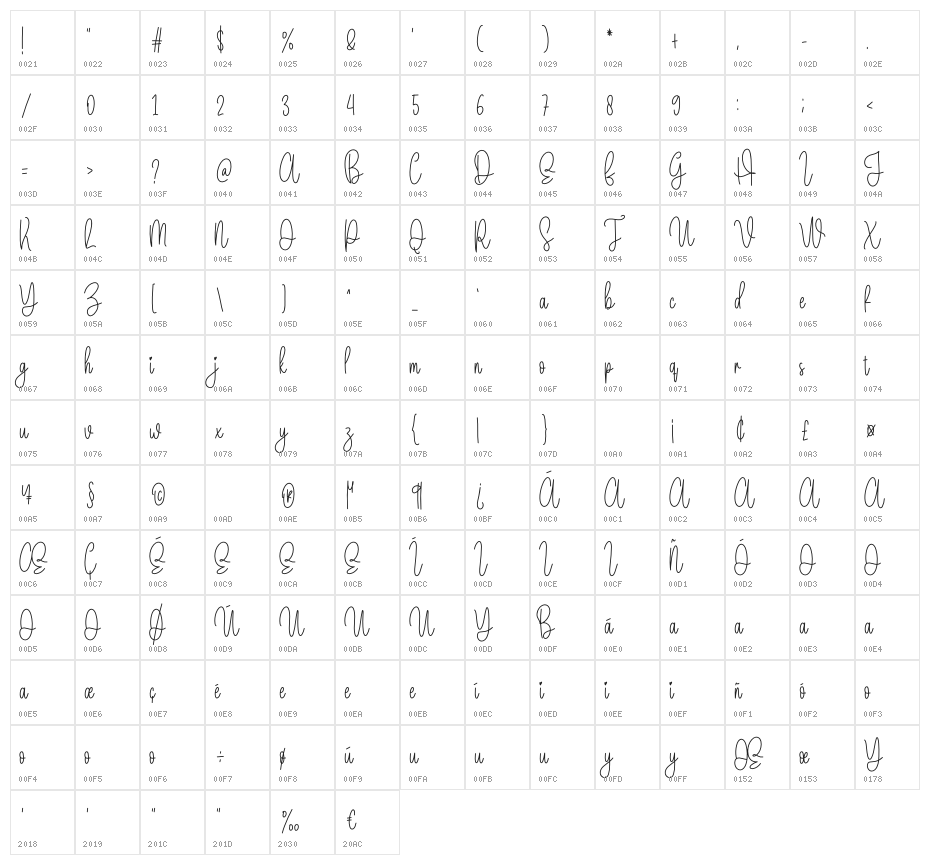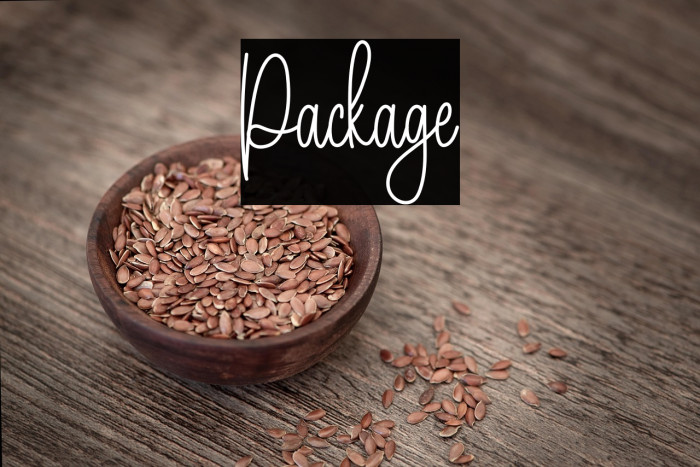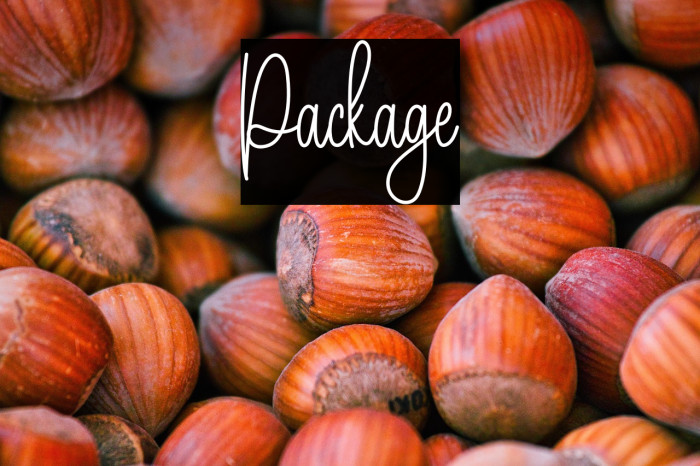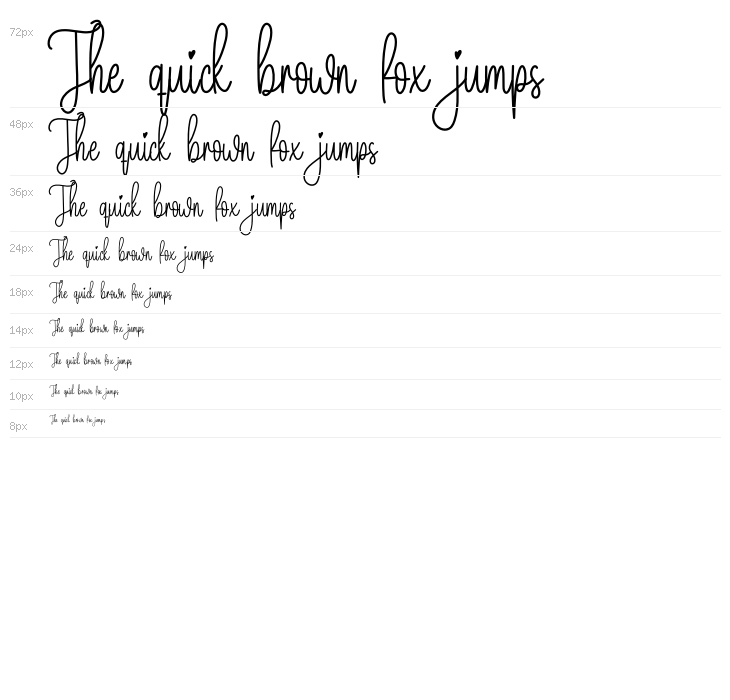
Package Font
| Anwendungsfall | Logos, Invitations, Greeting Cards |
| Vorgeschlagene Projekte | Ideal for invitations, greeting cards, personal branding, and creative projects that require a handwritten feel. |